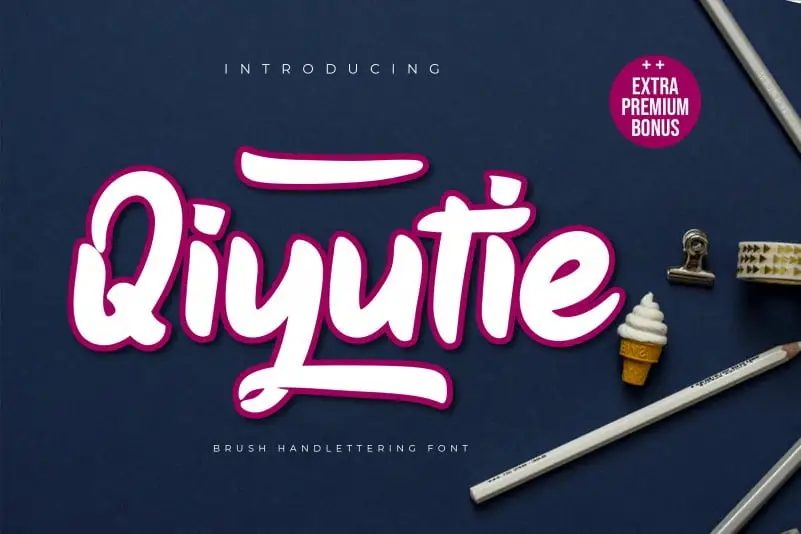
Qiyutie Script Font – Download Grátis
Qiyutie Script Font é uma tipografia fluída criada a partir de traços desenhados à mão livremente. Este font possui traços grossos que trazem ao seu design um tom sedutor e elegante, característica distintiva da escrita de mãos livres. Qiyutie é a escolha perfeita para estilos criativos, sua fluididade e harmonia tipográfica permitem que você expresse suas ideias de várias maneiras diferentes. Como fonte de script, ele oferece uma grande liberdade na criação do design, permitindo que os designers expressem sua criatividade através da forma e do movimento dos caracteres. Este é o tipo certo para quem busca um ar fresco e distintivo, combinando elegância e flexibilidade em cada letra.